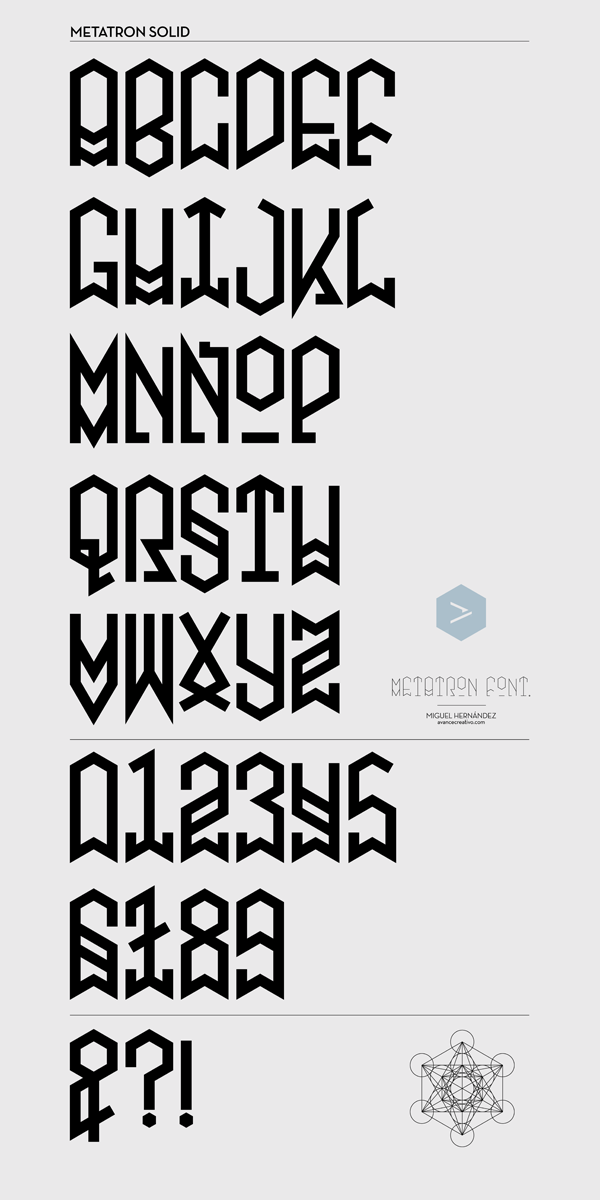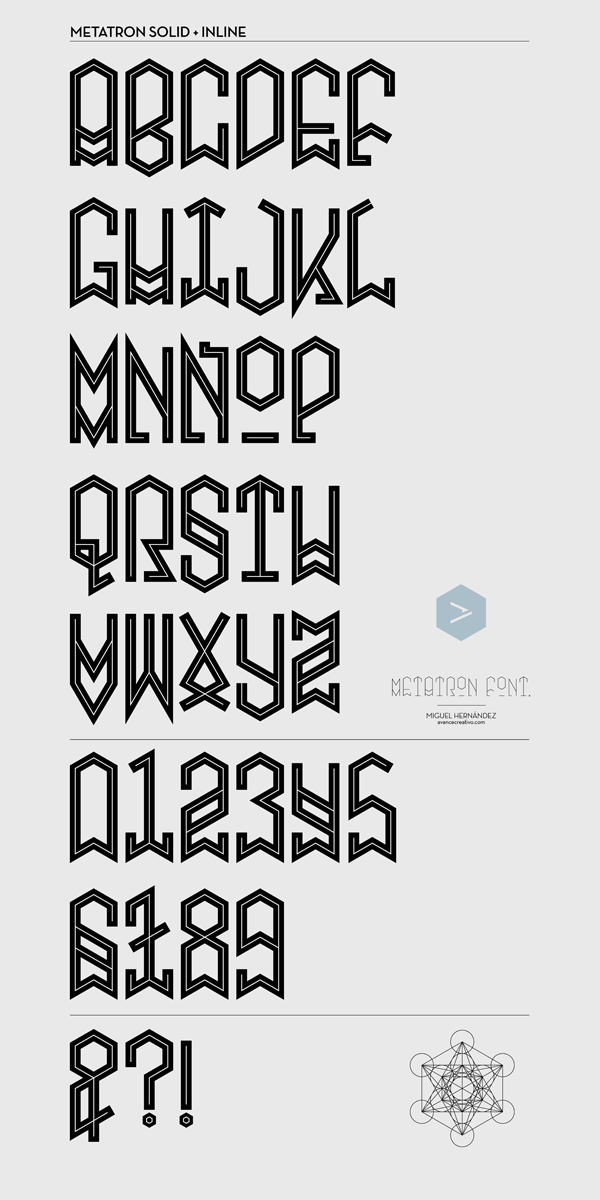
Metatron Font (Preview)
Basada en la geometría del cubo de Metatrón.
Metatron's Cube is a figure of sacred geometry, known as "in sacred geometry. Its name makes reference to Metatron, an angel mentioned in apocryphal texts including the Second Book of Enoch and the Book of the Palaces.
El cubo de Metatrón es una figura de la geometría sagrada, conocido como "La fruta de la vida". Su nombre hace referencia a Metatrón, un ángel que se menciona en textos apócrifos como el Segundo Libro de Enoc y el Libro de los Palacios.